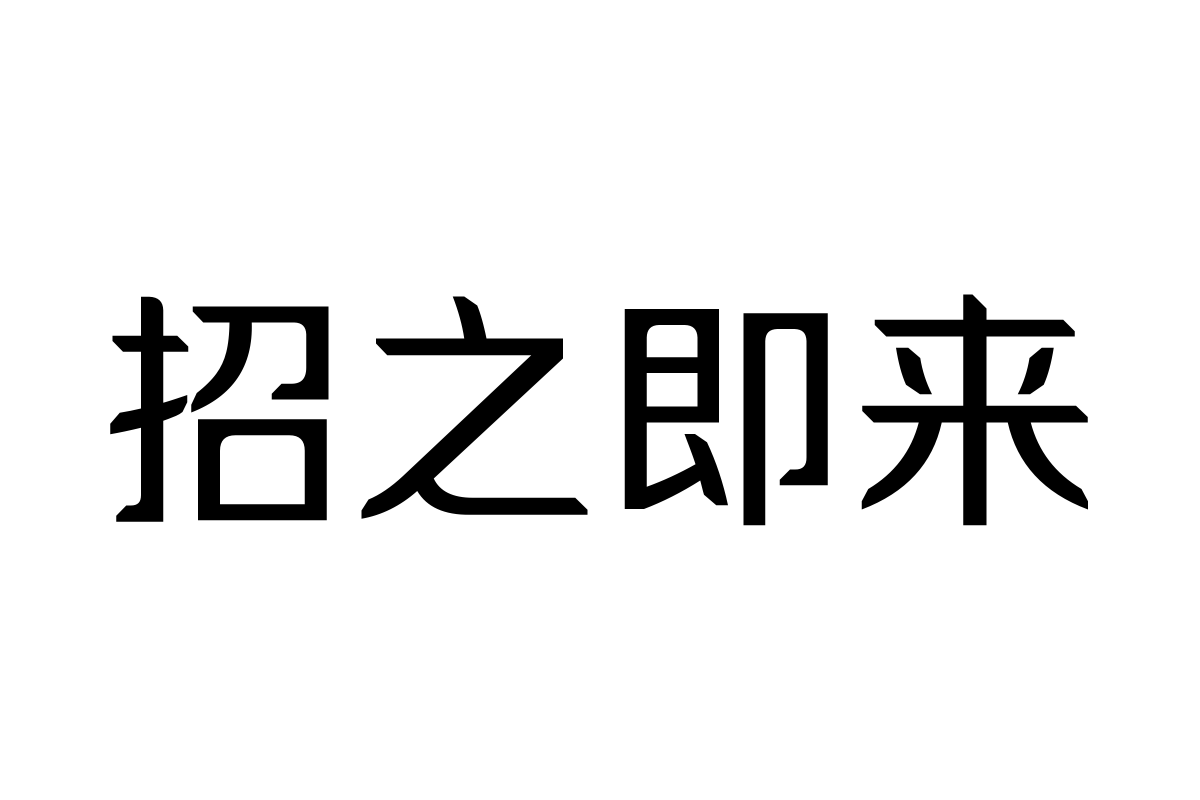
三极凌飞简体字体是一款由设计师精心打造的现代中文字体,具有独特的设计风格和丰富的表现力。这款字体采用了简洁的线条和清晰的结构,使得文字呈现出一种流畅而优雅的视觉效果。同时,它也能够很好地适应各种应用场景,无论是在网页设计、平面设计还是其他媒体制作中都能展现出良好的效果。
三极凌飞简体字体的特点在于其高度可读性和易用性,这使得它在各种文本编辑和排版工作中得到了广泛的应用。无论是标题、正文还是广告宣传等,都能够通过这款字体得到清晰、美观的呈现。此外,它还具有一定的个性和时尚感,能够为设计作品增添更多的艺术气息和创意元素。
总的来说,三极凌飞简体字体是一款非常优秀的中文字体,它不仅能够满足用户对于文字美观度的需求,还能够提升整体设计的品味和档次。无论是专业设计师还是普通用户,都可以从这款字体中感受到其带来的独特魅力和价值。